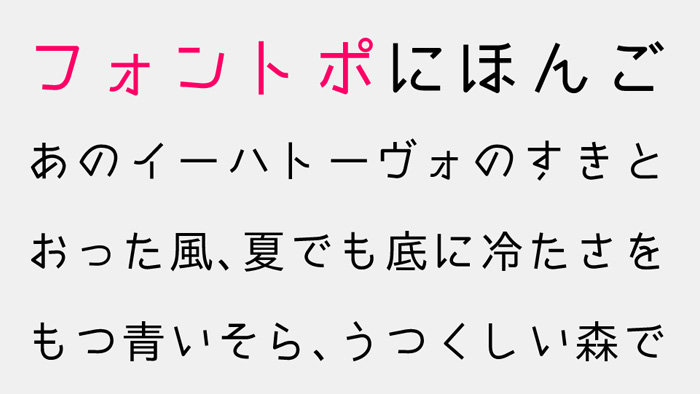
フォントポにほんごフォントは、文字に切り込みが入っているのが特徴的なデザインで、直線的で角ばっているユニークなゴシック体フォントです。
切り込みが入っていることで、ステンシル文字のようなかっこいい雰囲気を感じるデザインです。
ベタ打ちしただけでも味があるユニークな形をしているので、そのままロゴタイトルなどに使ってみても面白いかもしれません。
フォントポにほんご
収録文字は、ひらがな・カタカナ、漢字、英数記号で、漢字・英数字記号文字は源ノ角ゴシックで補われています。